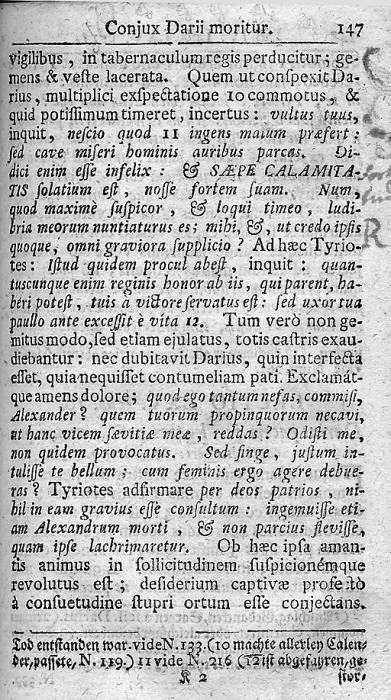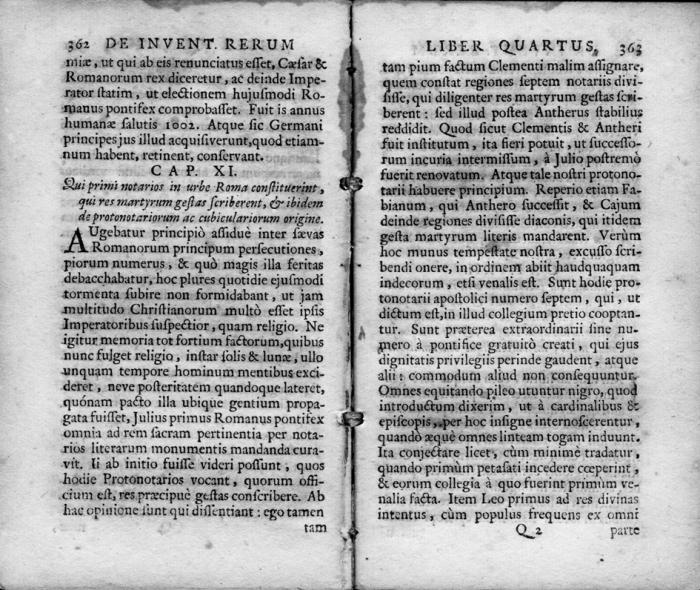
Zeileneinzug ohne Zeilenumbruch?
Hallo! Wie nennt man einen Einzug, der mitten im Text gesetzt ist, um einen neuen Gedanken abzutrennen? Ein Einzug ist es ja an sich nicht, denn es gibt keinen Zeilenumbruch. Und “Textlücke” möchte ich es nicht nennen.
Ist das nicht einfach dem Blocksatz geschuldet?
Der Drucker setzte die Wörter ziemlich kompreß, und unschöne Lücken durch den Blocksatz gibt es so gut wie keine, und wenn, dann unscheinbare, der Drucker hat gute Arbeit geleistet. Es gibt im Text immer wieder absichtlich gesetzte “Abstände”, und ich wüßte gerne wie man die typographisch nennt.
Mein Lateiner sagt, dass das bei Drucken häufiger mal vorkommt, um einen Satzanfang deutlich zu machen. Er kennt aber keinen „offiziellen“ Fachbegriff für sowas. Wir würden das einfach Spatium nennen.
Spatium klingt fachlich und spezifisch …
Nein, »Spatium« kann hier nicht passen. Ein Spatium ist ein sehr kleiner Abstand (1p). Eher noch würde »Geviert« passen, aber der oben gezeigte Abstand ist sogar noch größer als ein Geviert; da hat, eine 10-p-Schrift unterstellt, jemand zusätzlich zum regulären Wortabstand einen Cicero-Quadraten zwischengeschlagen. Außerdem sind Spatium und Geviert ja Begriffe, welche die satztechnische Seite der Sache beschreiben, während die Fragestellung, wenn ich sie richtig verstehe, ja eher auf die ästhetische / microtypographische / verlagstechnische Seite zielt.
Hier nochmal eine weitere Textstelle in der Gesamansicht:
Der große Wortzwischenraum nach dem Schlusspunkt eines Satzes war nach den älteren Satzregeln Bestandteil des „Ausschließens“, das genau geregelt war.
Nach diesen Ausschließregeln wurde bereits beim Setzen (vor dem Ausschließen der Zeile) nach dem Schlusspunkt eines Satzes der Wortzwischenraum verdoppelt.
Die Regeln galten noch Anfang bis ca. Mitte des vorigen Jahrhunderts.
Das „Ausbringen“ (Vergrößerung der Wortzwischenräume) und das „Einbringen“ (Verkleinern der Wortzwischenräume) wird im satztechnischen Lexikon genau beschrieben.
Weniger genau geregelt war das beim Satz sehr alter Bücher. Die Zwischenräume nach Schusspunkten uferten manchmal unproportional aus, wie in deinem Beispiel. Vor verschiedenen Satzzeichen wurden mehr oder weniger stake Spatien gegeben, ohne einer genauen Regel zu folgen.
So kam es vor, dass auf einer Seite vor Satzzeichen, ausgenommen Schlusspunkt,  ein kleiner Zwischenraum gesetzt wurde und auf der nächsten Seite alle Satzzeichen kompress zum Text gesetzt wurden.
Ob es für diese „Lücke“ nach dem Schlusspunkt eine spezielle Bezeichnung gab, kann ich nicht sagen – sie ist wahrscheinlich einfach nur Bestandteil der „Ausschließregeln“.
Hallo Erwin. So wie ich dich verstehe, beschreibst du den generellen Umgang mit Wortzwischenräumen. Man vergrößte generell den Wortabstand nach Satzpunkten, um diesen mehr optisches Gewicht verleihen. Bei diesem Druckwerk ist es ja nun aber so, daß es sich um einen nur sporadisch gesetzten Wortabstand handelt, der geradezu riesig ist und anscheinend absichtlich gesetzt wurde, um einen neuen Textabschnitt zu abzugliedern. Einen neuen Abschnitt, der etwas gewichtiger ist als bloß ein neuer Satz, jedoch nicht ganz so abrupt wie ein Absatz (mit Zeilenumbruch).
Das scheint bei Büchern aus dem englischen Sprachraum teilweise auch heute noch gebräuchlich zu sein.
Bei diesem Druckwerk ist es ja nun aber so, daß es sich um einen nur sporadisch gesetzten Wortabstand handelt, der geradezu riesig ist und anscheinend absichtlich gesetzt wurde, um einen neuen Textabschnitt zu abzugliedern. Einen neuen Abschnitt, der etwas gewichtiger ist als bloß ein neuer Satz, jedoch nicht ganz so abrupt wie ein Absatz (mit Zeilenumbruch).
Dass ein Absatz mit einem Zeilenumbruch einhergeht, ist nur nach unserem heutigen Verständnis so. Absatz bezeichnet ursprünglich nicht den Umbruch, sondern das Absetzen im Textfluss bzw. das Trennen von Abschnitten. Das kann mit farbiger Abschnittsmarke erfolgen, mit großer Lücke, mit Umbruch oder was auch immer.
Formal liegt hier also auch nur ein Absatz vor. Dass so eine Lücke-deutlich-größer-als-ein-Leerzeichen-die-einen-Absatz-markiert-aber-nicht-so-stark-wie-ein-Umbruch-wirken-soll einen eigenen Namen hätte, wüsste ich allerdings nicht.
Vielleicht geht dies aus meinem vorigen Beitrag nicht genau hervor.
Große bis sehr große Abstände nach Schlusspunkten waren In alten Büchern zum Zwecke der Satzgliederung üblich. Oft „entsorgte“ man deshalb den verbleibenden Leerraum nach dem Schlusspunkt und wenn noch etwas übrig blieb, bekamen auch die übrigen Satzzeichen noch ein Spatium verpasst.
So genau nahm man es nicht mit dem Aufteilen der Leerräume.
Und so sehe ich auch den großen Zwischenraum in deinem Beispiel: Schmales Format, wenig Möglichkeit zur Aufteilung des Leerraumes, also alles nach dem Schlusspunkt hinein. Und das ohne besonderen Grund.
Ich meine mal gelesen zu haben, dass der Ursprung dieser großen Absatzlücken aus der Zeit der Inkunabeln stammt. Auch wenn die Texte damals weitgehend gesetzt wurden, wurde die Rubrizierung meist von einem Rubrikator übernommen. Dazu gehörte auch das Malen des Alineas zur Kennzeichnung eines neuen Absatzes. Aus verschiedenen Gründen kam es jedoch vor, dass die farbigen Rubriken nicht eingetragen wurden und sich so diese Lücke als »unsichtbares« Absatzzeichen etablieren konnte.